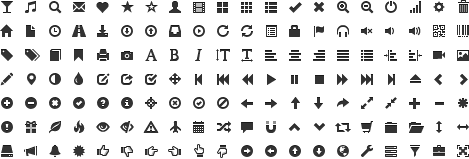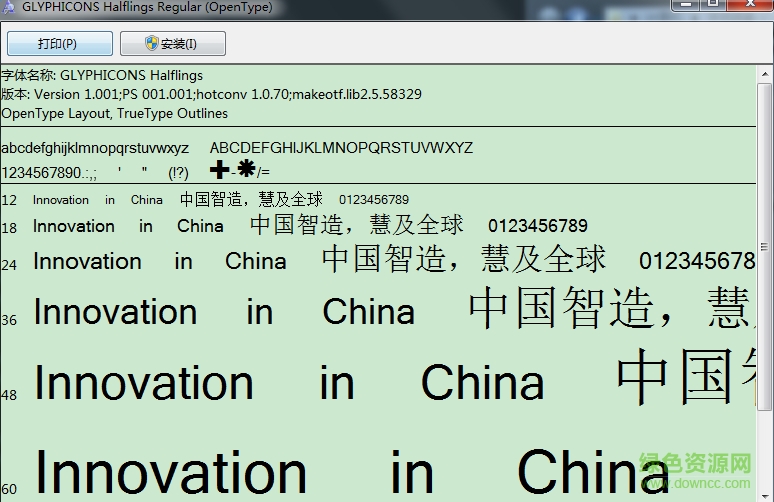
glyphicons-halflings-regular.ttf是一款非常實(shí)用的矢量字體,這個(gè)字體文件能夠兼容各種字體符號,是電腦的必備字體,需要的朋友歡迎來綠色資源網(wǎng)下載。
采用這種字體,我們可以避免網(wǎng)站制作中采用好多圖片,一方面解決了瀏覽器的兼容性問題。另一方面,這些字體都是矢量字體,我們只要在調(diào)整這些圖標(biāo)時(shí),將他們的字體大小以及顏色,我們就可以解決很多不是圖片的圖標(biāo)了。